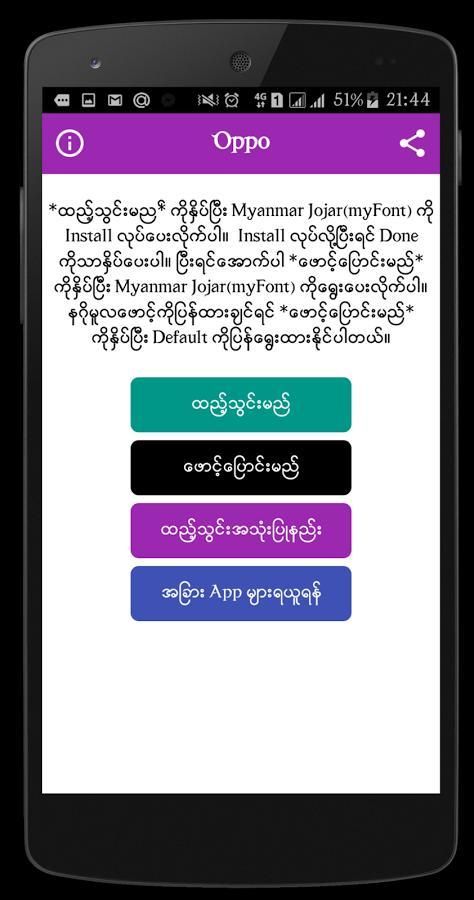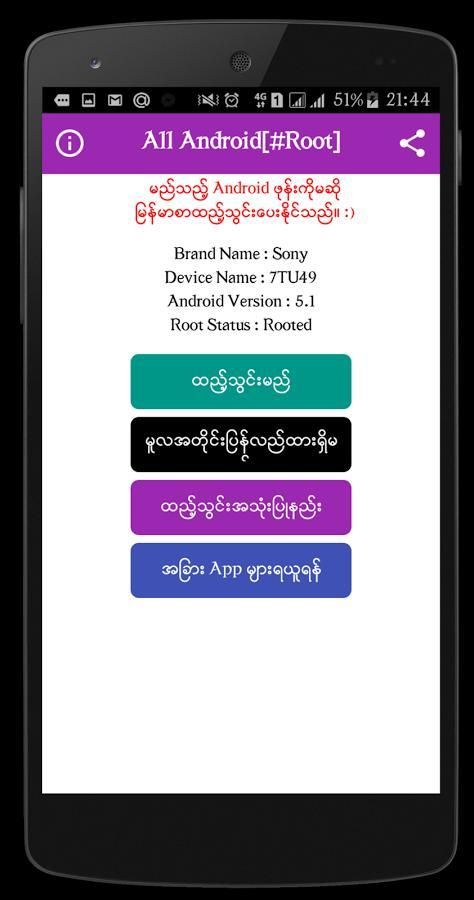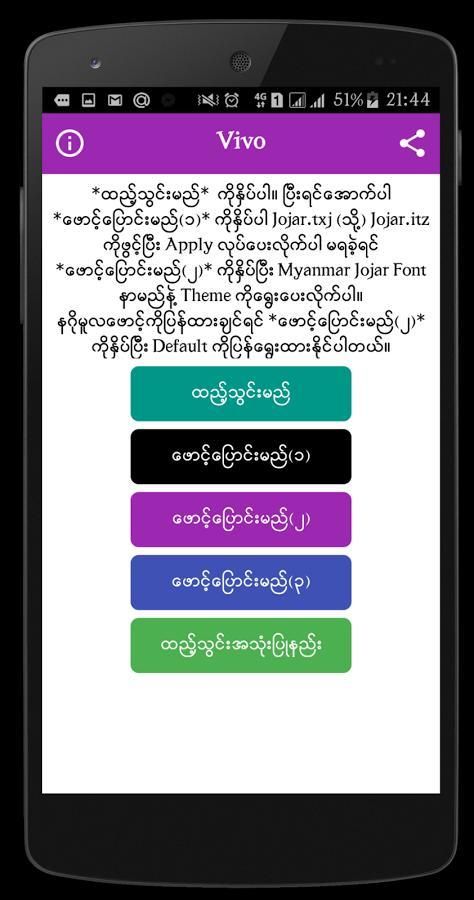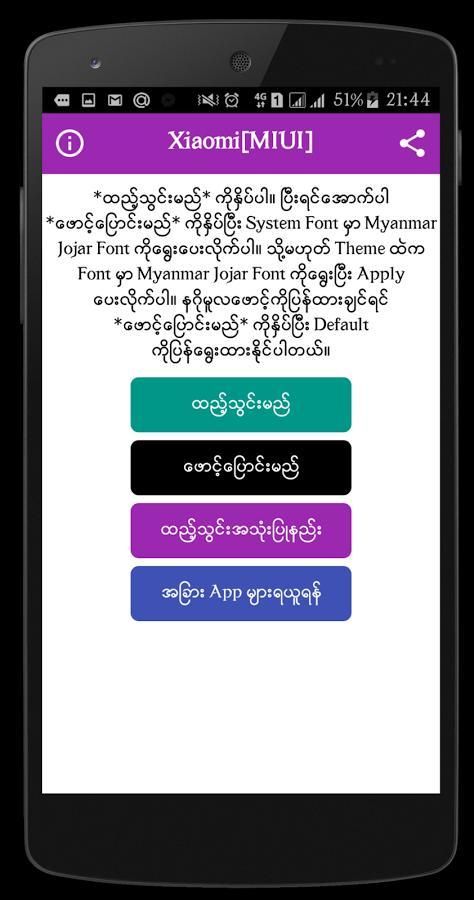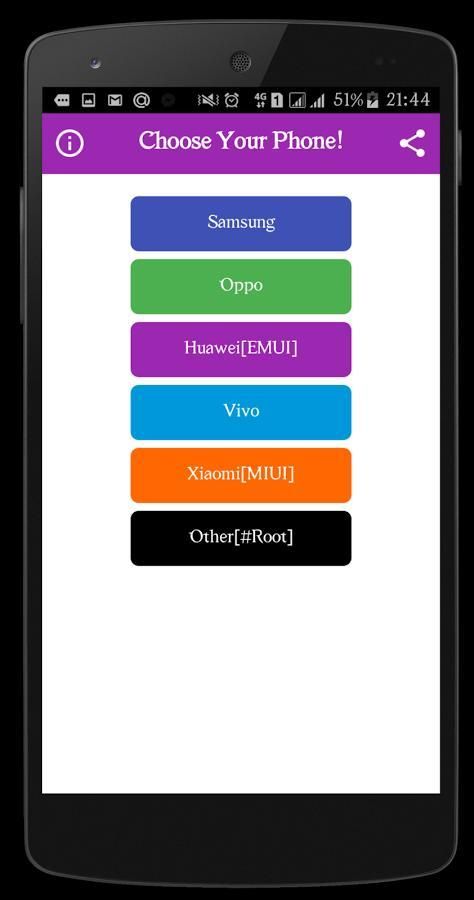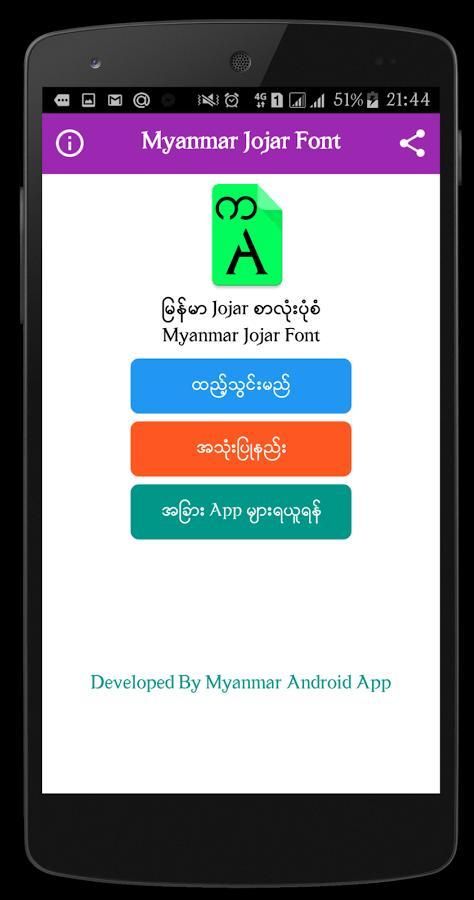
Myanmar Jojar Font
"Myanmar Jojar Font" Root မလိုထည့္သြင္း ျမန္မာစာလုံးအလွတစ္ခုျဖစ္ပါသည္။
ဖုန္းမွာျမန္မာစာလုံးအလွသုံးခ်င္သူမ်ားအတြက္
Myanmar Jojar ဆိုတဲ့စာလုံးအလန္းေလးတစ္ခုပါ။
အရမ္းလန္းပါတဲ့စာလုံးပုံစံေလးပါ။